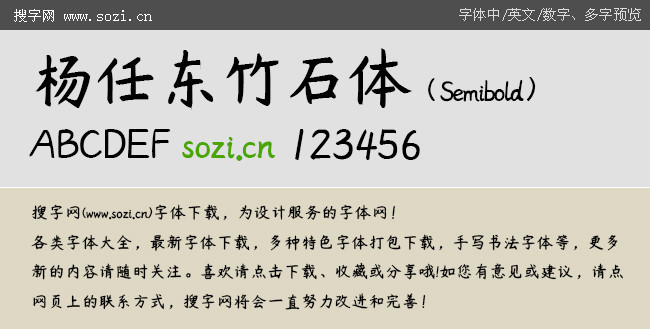
楊任東竹石體Semibold
搜字網(wǎng)給大家提供一款楊任東竹石體Semibold中文字體下載。楊任東竹石體于2017年4月26日世界知識(shí)產(chǎn)權(quán)日正式發(fā)布,本字體按照GB2312-80書(shū)寫(xiě),并增補(bǔ)了少量常見(jiàn)漢字;整套字體有7個(gè)字重,共計(jì)50000余個(gè)字符,本套字體授權(quán)全社會(huì)免費(fèi)商用,意味著您可以將其無(wú)限制地捆入您的商業(yè)產(chǎn)品中,如海報(bào)、包裝、logo、網(wǎng)頁(yè)、APP等。
• 風(fēng)格類別: 手寫(xiě)書(shū)法體